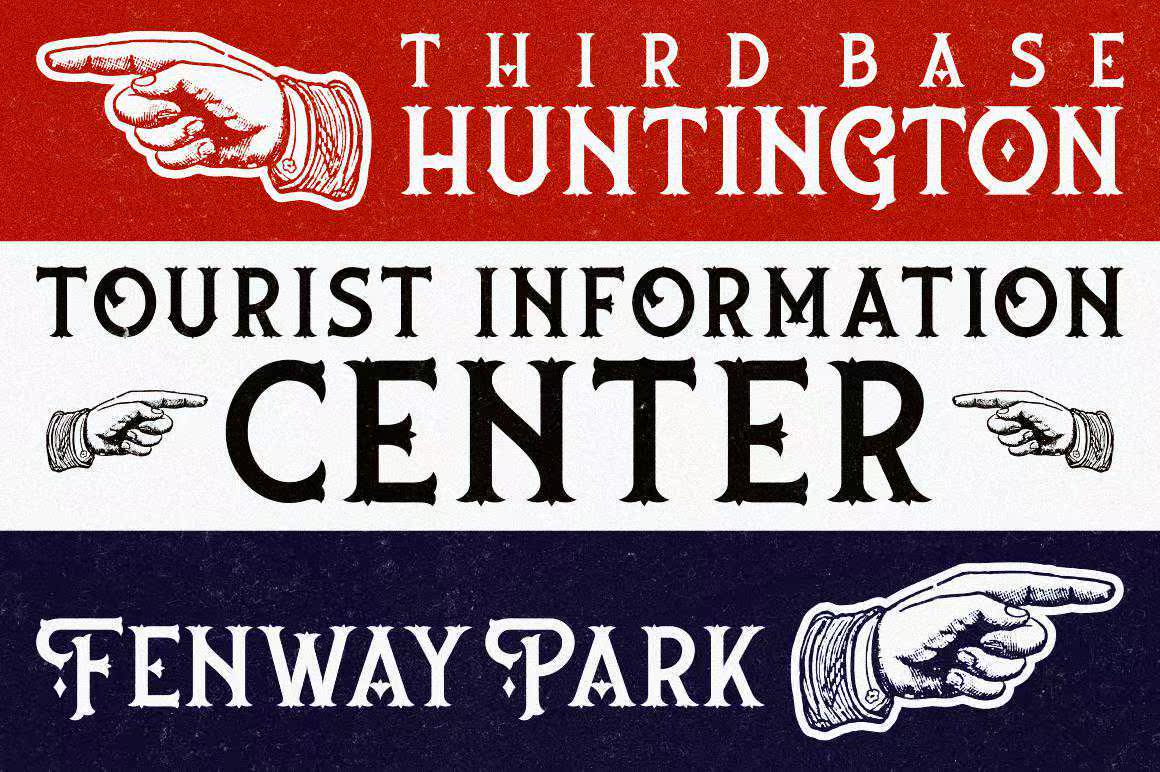
介绍最新的字体;Nufced,肛门帽,这会让你的设计品味感到愉悦。运动和广告之间的不协调,这是美国广告制作者的灵感。Nufcedisasrikenother,它在不增加流动性和灵活性的情况下,给人强烈而敏锐的感觉。适合任何港口和葡萄酒,设计MED项目。介绍最新的字体;Nufced,肛门帽的外观会让你的设计品味感到愉悦。运动和广告之间的差异是由美国广告制作者激发出来的。Nufcediaseric,它在不增加流动性和灵活性的情况下,给人强烈而敏锐的感觉。适合任何港口和葡萄酒设计MED项目。